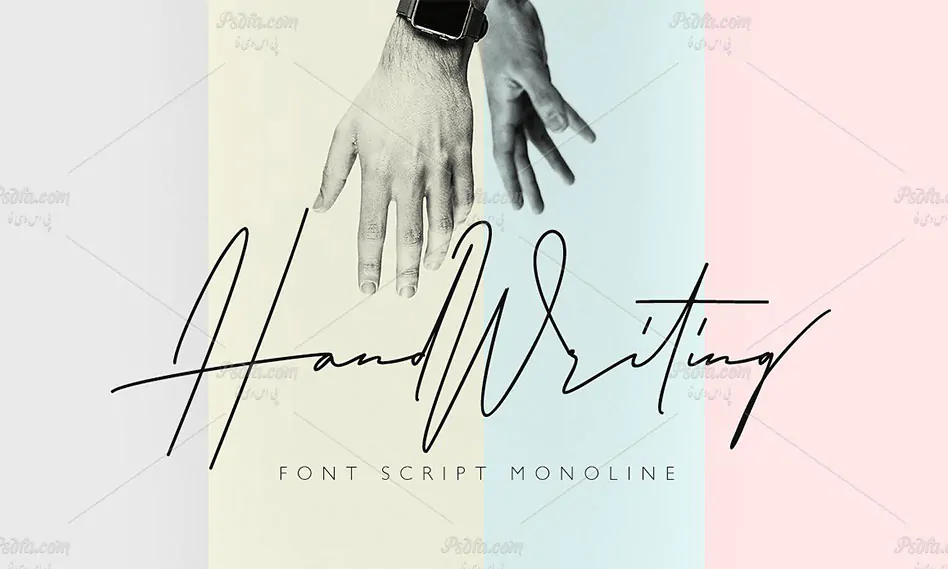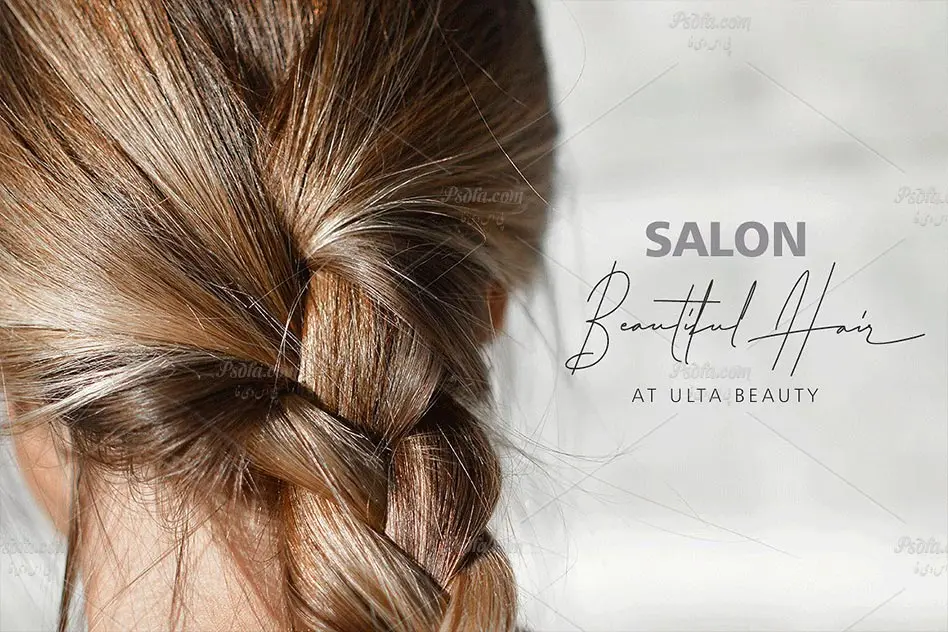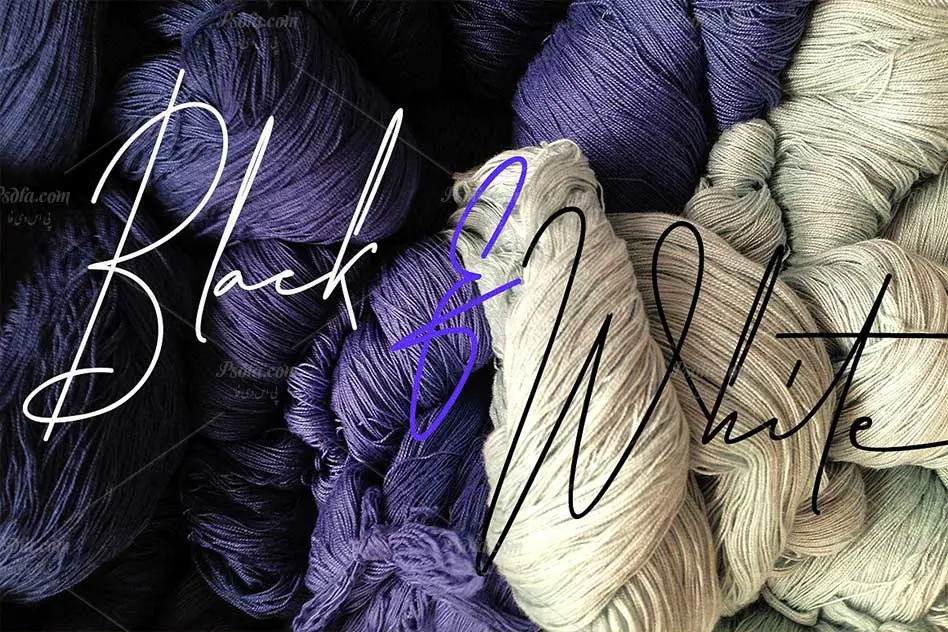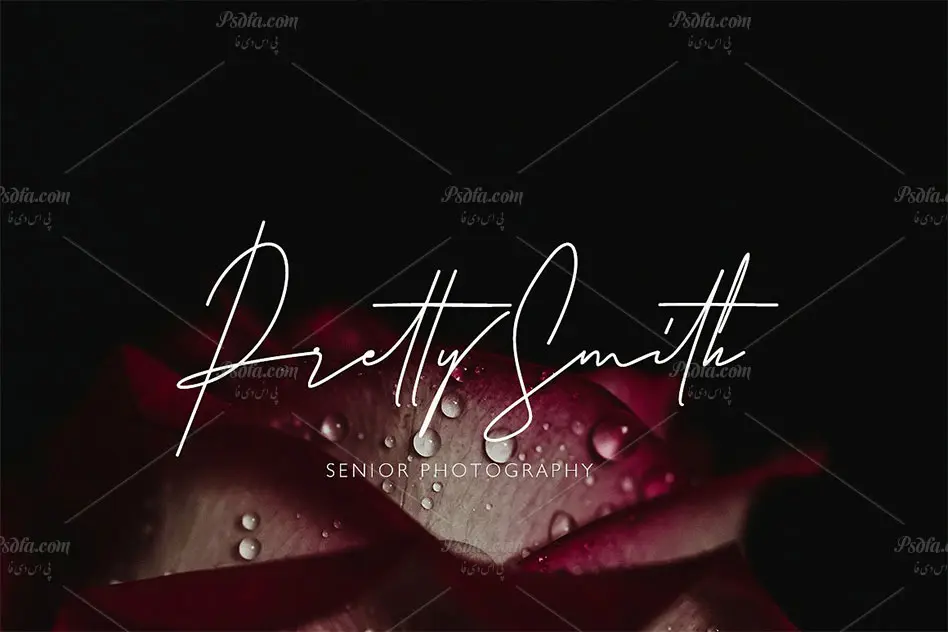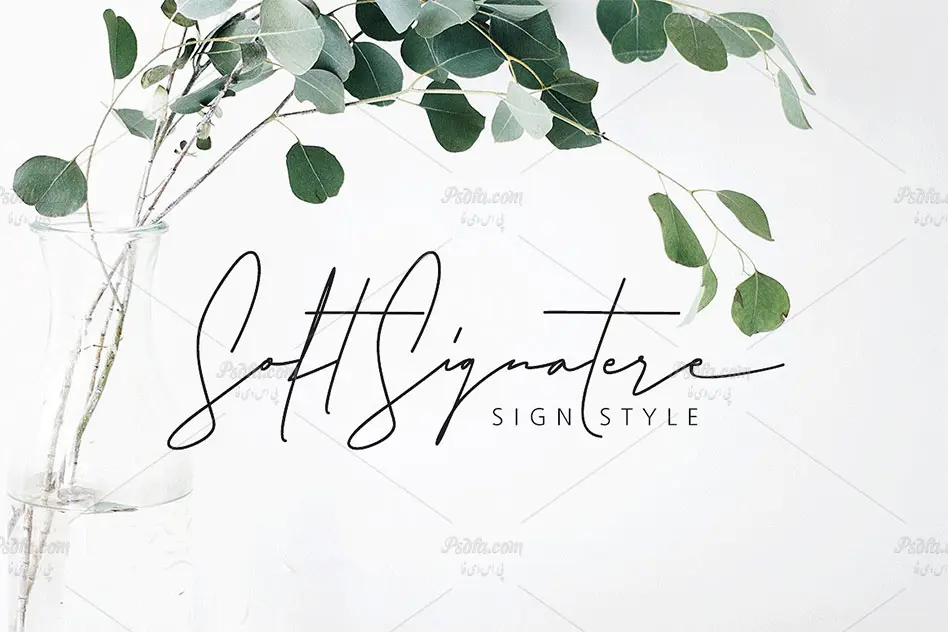
فونت انگلیسی Handwritting طراحی شده به صورت دستنویس
فونت انگلیسی Handwritting
در این مطلب شاهد فونت انگلیسی Handwritting طراحی شده به صورت دستنویسی می باشید. این فونت فوق العاده زیبا با 2 فرمت otf و ttf در سایت قرار داده شده است که پس از نصب آن در پوشه فونت های سیستم قادر به استفاده از آن در تمام نرم افزارهای گرافیکی و ویرایشگر متن از جمله نرم افزار فتوشاپ ، مجموعه نرم افزار آفیس و … می باشید. از این فونت زیبا که به صورت دستنویسی طراحی شده است می توان در موارد گوناگون از جمله استفاده در امضاء ، استفاده در استودیوهای گرافیکی ، طراحی پوستر ، طراحی انواع قاب عکس و … استفاده نمود.